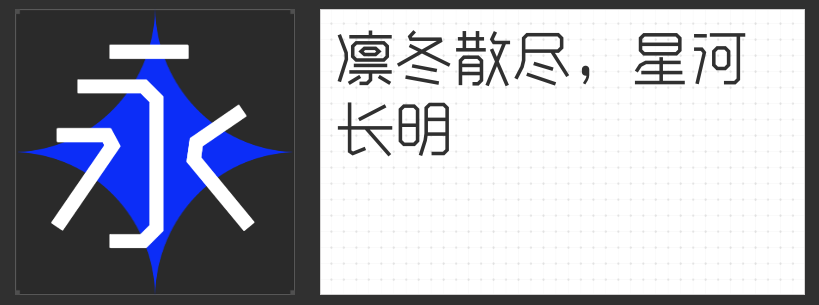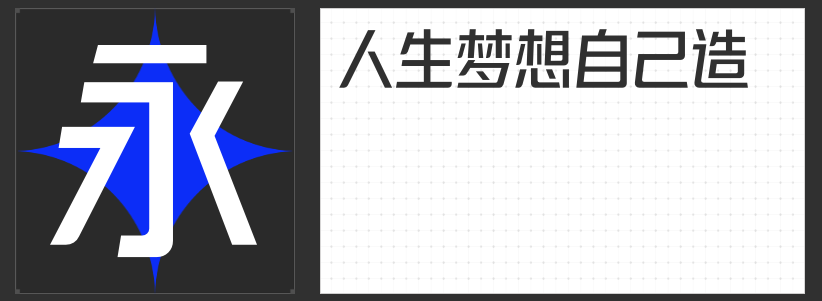
四款高辨识度字体,为短视频注入视觉张力与节奏感
短视频设计需要兼顾信息传递效率与视觉吸引力,而字体的选择往往决定了画面的第一印象。无论是动态标题、字幕还是品牌标识,一款风格契合的字体能瞬间提升内容质感。以下四款字体以独特的设计语言与视觉表现力,成为短视频创作的“加分利器”。
一、高手庆科智雅体 常规
这款字体以直线为核心,中宫略大、布白均匀,笔画视觉等粗却通过连笔折笔打破单调感。切口处理弱化了尖锐感,整体呈现出克制而精致的现代感。其西文符号与中文风格高度统一,适合需要传递专业感又不失亲和力的场景,如知识科普、生活记录类短视频的标题或字幕,能在快速浏览中保持清晰可读性。
二、励字钧线黑简 微黑
以15°斜度构建动态平衡,转折处利落的折角设计赋予字体向前冲刺的视觉张力。全直线结构通过细节优化降低阅读疲劳,同时符合当代极简审美趋势。这款字体在运动、科技类短视频中能强化速度感与科技感,尤其在快节奏剪辑中,其简洁有力的笔画能瞬间抓住观众注意力,成为画面中的视觉锚点。
三、励字造梦简 中粗
灵感源自“青春筑梦”,左侧倾斜与右侧竖直的不对称设计模拟出仰望摩天楼的透视效果,棱角分明的直线轮廓充满力量感。这款字体适合音乐、旅行类短视频的标题设计,其夸张的透视感能营造空间纵深感,与动态画面形成呼应,让文字本身成为讲述故事的视觉符号。
四、造字侠热辣隶简
将隶书的扁宽结构与现代设计语言结合,笔画线条简洁明快却暗藏力量感。撇捺的粗细过渡自然,横笔开张如展翅飞鸟,竖钩以直线概括书写力度。这款字体在国潮、文化类短视频中能传递历史厚重感与当代活力,尤其适合作为品牌标识或文化主题的标题,让传统文字焕发新生机。
这四款字体以独特的设计语言满足短视频多样化的视觉需求,无论是追求现代感、动态张力还是文化底蕴,都能找到与之匹配的表达方式,为内容创作注入更多可能性。